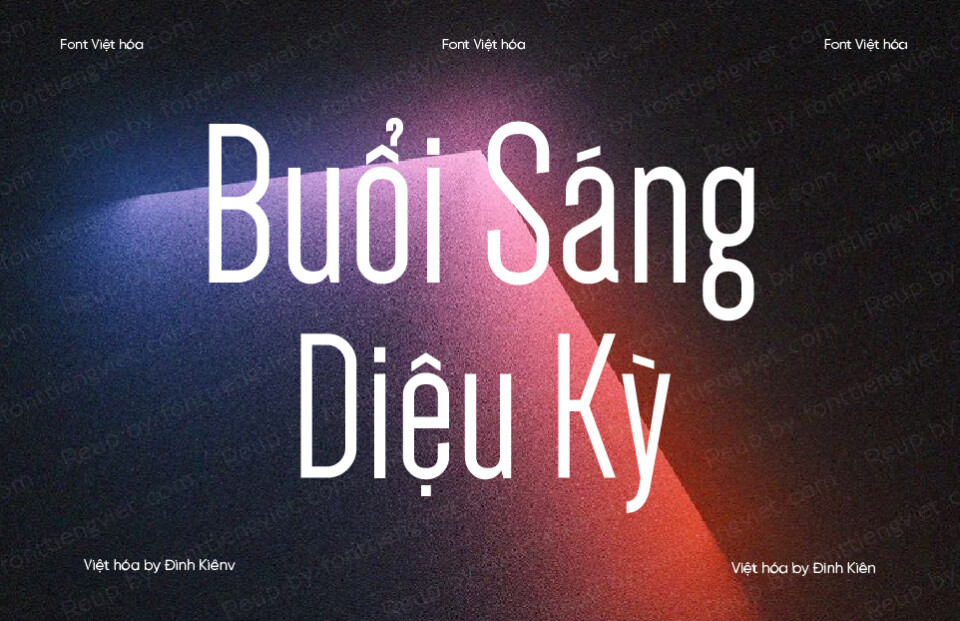
Giới thiệu về Font Việt hóa UTM Dense trong thiết kế đồ họa
Trong thế giới sáng tạo, việc lựa chọn Font Chữ phù hợp đóng vai trò then chốt để truyền tải thông điệp hiệu quả. Font Việt hóa UTM Dense là một trong những bộ phông chữ thuộc dòng Sans-serif (không chân) được yêu thích nhất hiện nay. Với đặc điểm các nét chữ được nén lại theo chiều dọc, bộ font này mang đến vẻ ngoài thanh mảnh nhưng vẫn vô cùng mạnh mẽ và hiện đại. Đây là lựa chọn lý tưởng cho những người làm thiết kế muốn tối ưu hóa không gian hiển thị mà vẫn giữ được sự tinh tế, chuyên nghiệp trong từng sản phẩm của mình.
Tại sao Font Việt hóa UTM Dense lại được ưa chuộng?
Lý do chính khiến Font Việt hóa UTM Dense trở nên phổ biến là khả năng hiển thị rõ nét ngay cả ở kích thước nhỏ. Cấu trúc chữ gọn gàng giúp người dùng dễ dàng ứng dụng vào các tiêu đề poster, biểu ngữ hoặc giao diện ứng dụng di động. Đặc biệt, phiên bản Việt hóa đã được căn chỉnh bảng mã chuẩn, giúp các bạn học sinh và giáo viên soạn thảo văn bản tiếng Việt mà không lo bị lỗi dấu hay sai định dạng kỹ thuật.
Ứng dụng thực tế của bộ font UTM Dense
Sử dụng trong giáo dục và quảng cáo
Đối với môi trường học đường, bộ font này thường xuyên xuất hiện trên các trang bìa tiểu luận, báo tường hoặc slide bài giảng điện tử. Sự gọn gàng của nó giúp nội dung trở nên ngăn nắp và dễ theo dõi hơn. Trong lĩnh vực marketing, UTM Dense là “vũ khí” đắc lực để tạo ra những dòng headline ấn tượng, thu hút ánh nhìn của khách hàng ngay từ giây đầu tiên.